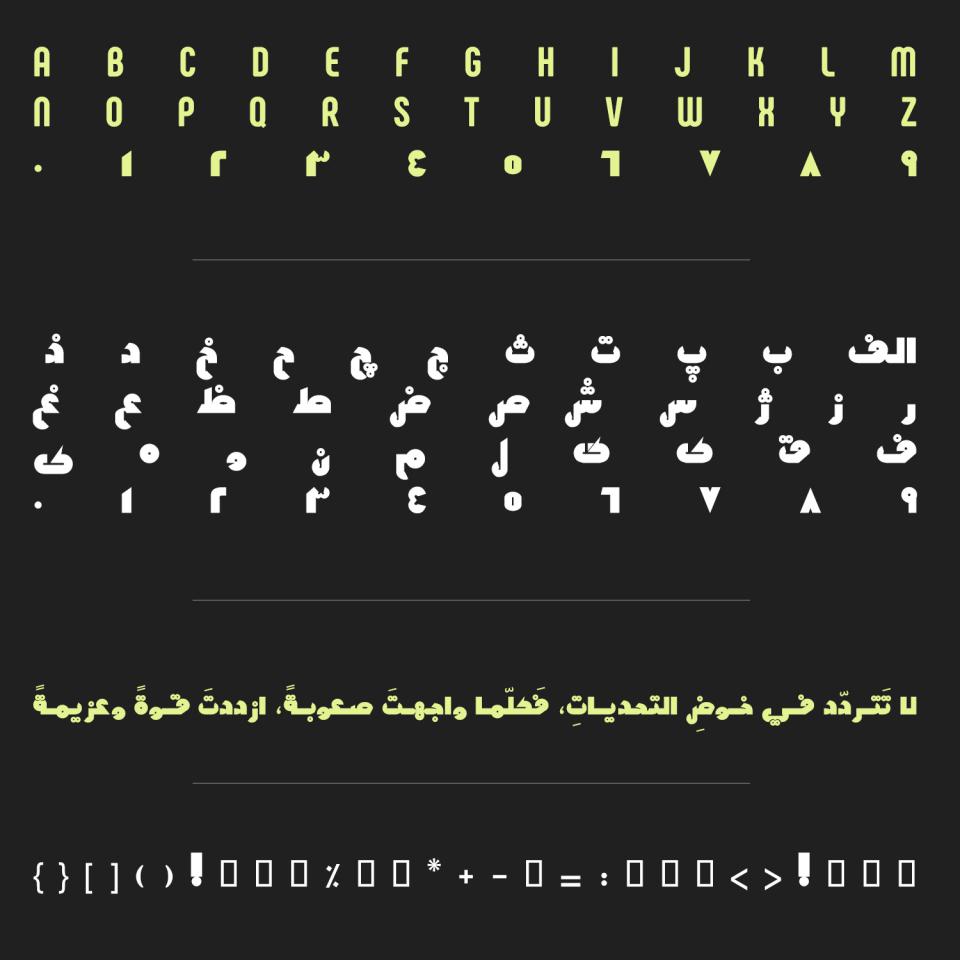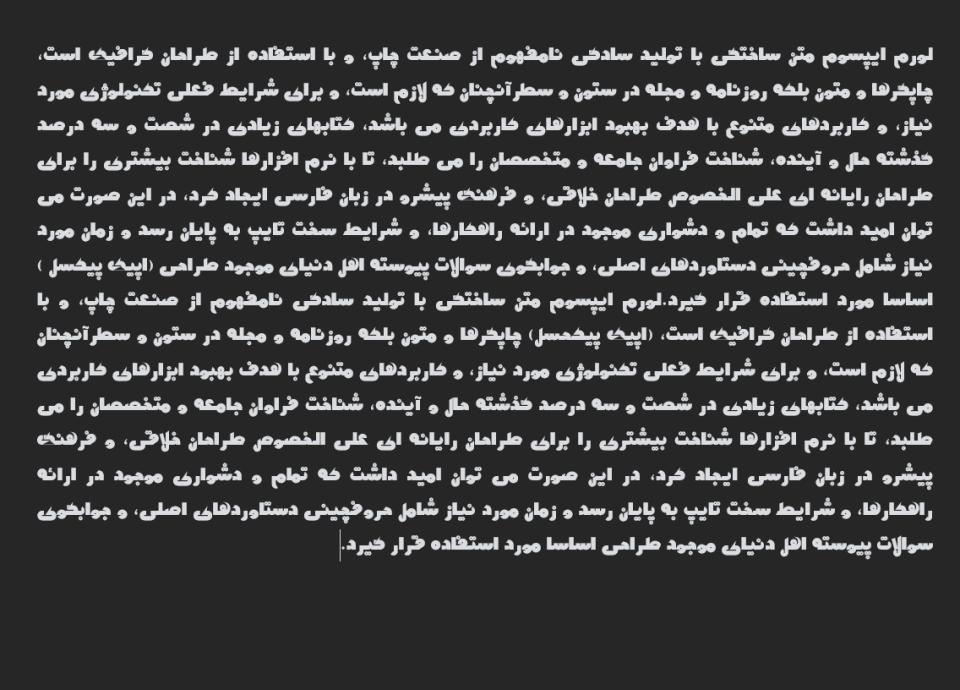
2 فونت سیاه فارسی
فونت سیاه فارسی، با طراحی خاص و منحصربه فرد خود، جلوه ای قدرتمند و چشمگیر به نوشته های شما می بخشد. این فونت با ضخامت و سیاهی متمایز، برای ایجاد عناوین جذاب، لوگوتایپ های حرفه ای و طراحی های گرافیکی مدرن ایده آل است. تصور کنید نوشته های شما با این فونت، چقدر در نگاه اول تاثیرگذار خواهند بود؛ گویی که با یک ماژیک ضخیم و مشکی روی کاغذ نوشته شده اند.
این فونت رایگان، به راحتی در تمامی نرم افزارهای طراحی و ویرایش متن قابل استفاده است و به شما این امکان را می دهد که بدون هیچ محدودیتی، خلاقیت خود را به نمایش بگذارید. اگر به دنبال فونتی هستید که نوشته هایتان را برجسته و متمایز کند، فونت سیاه فارسی بهترین انتخاب برای شماست. این فونت نه تنها ظاهر زیبایی دارد، بلکه به دلیل خوانایی بالا، تجربه کاربری بهتری را نیز فراهم می کند.
با دانلود فونت سیاه فارسی، به سادگی می توانید پروژه های خود را از سایرین متمایز کنید و حس قدرت و اعتماد را به مخاطب القا کنید. این فونت برای طراحی پوستر، کارت ویزیت، بنر و هر نوع طراحی دیگری که نیاز به تاکید و جلب توجه دارد، بسیار مناسب است. پس فرصت را از دست ندهید و همین حالا این فونت رایگان و کاربردی را دانلود کنید و به نوشته های خود جان تازه ای ببخشید.